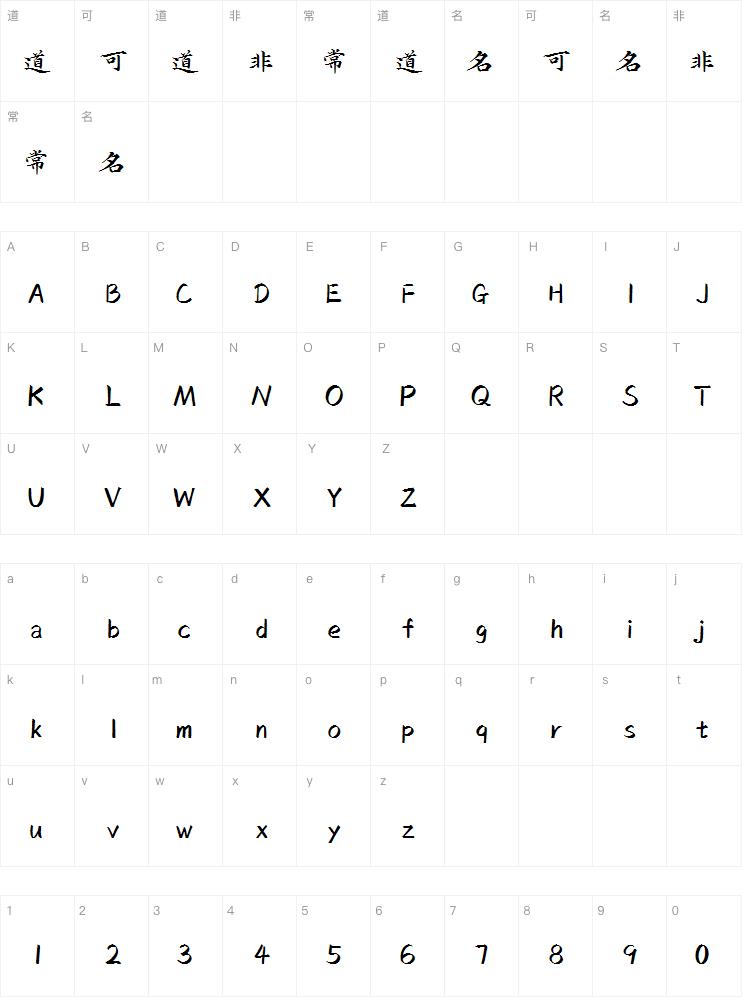
字魂贵州省博物馆联名体
字魂贵州省博物馆联名
字魂贵州省博物馆联名体灵感源自贵州省博物馆的文化藏品——“清郑珍勘定本王兰上诗赋稿”,同时借鉴了“清光绪宣统年间内府钞本”的字迹,用自古以来记录文稿的小楷为基础,逐步刻画出清腴华美的线条,赋予这款字体虚和简静的气息。整款字体笔调自然、秀气乃出,结构精致而清晰。在追求每个字高度美感的同时,段落中的排列则保持了端庄与平衡、工整与匀称,尽显中国字的独特魅力。尺幅虽然不大,方寸的笔画之间,气象万千。该字体适用于文创、文化宣传等场景。
字魂贵州省博物馆联名体